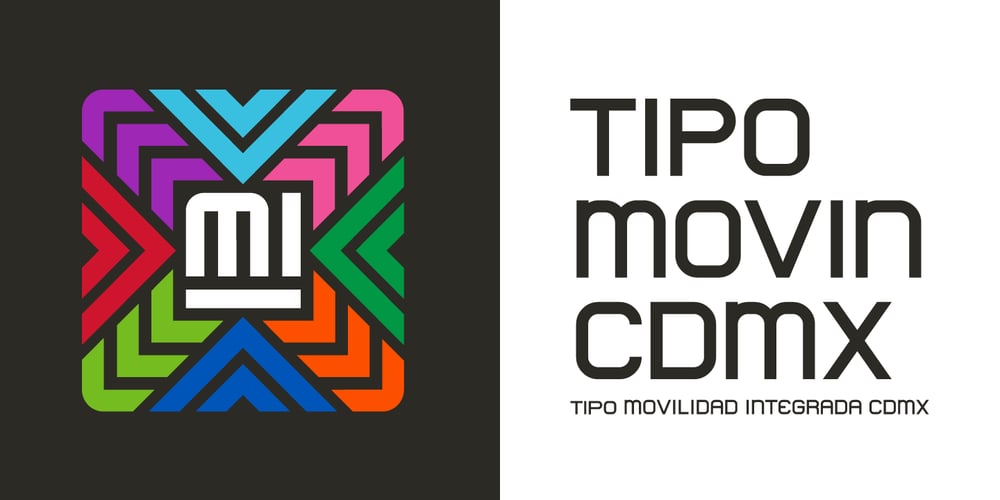
Tipo Movin CDMX
Tipo Movin CDMX font
Tipo Movin CDMX Font Family was designed by Francisco Arellano and published by Ixipcalli. Tipo Movin CDMX contains 1 styles and family package options. La versión propuesta por la SEMOVI (Secretaria de Movilidad) es un estilo más angosto y ortográfico, creadó con la finalidad de aligerar las aplicaciones tipográficas del sistema. Se emplea oficialmente en todas las aplicaciones del sistema de Movilidad Integrada de la Ciudad de México. El creador de la tipografía es Lance Wyman.En esta edición, los tipos minúsculas son una adaptación “no oficial” para el Tipo Movin CDMX, enriqueciendo la tipografía a un estilo visual de altas y bajas, por lo que se prescinde del diseño base como trabajo propio para enfatizar los tipos minúsculas exclusivamente, además de que se han añadido algunos caracteres de acentuación extendiendo su uso a otros lenguajes. Los tipos son una nueva propuesta por Ixipcalli en el presente año 2023.The version proposed by SEMOVI (Secretary of Mobility) is a narrower and more orthographic style, created with the purpose of lightening the typographic applications of the system. It is officially used in all the applications of the Integrated Mobility system of Mexico City. The creator of the typeface is Lance Wyman.In this edition, the lowercase types are an “unofficial” adaptation for the Tipo Movin CDMX, enriching the typography to a visual style of highs and lows, so the base design is dispensed with as my own work to emphasize the lowercase types exclusively, In addition, some accentuation characters have been added, extending their use to other languages. The types are a new proposal by Ixipcalli in the current year 2023.